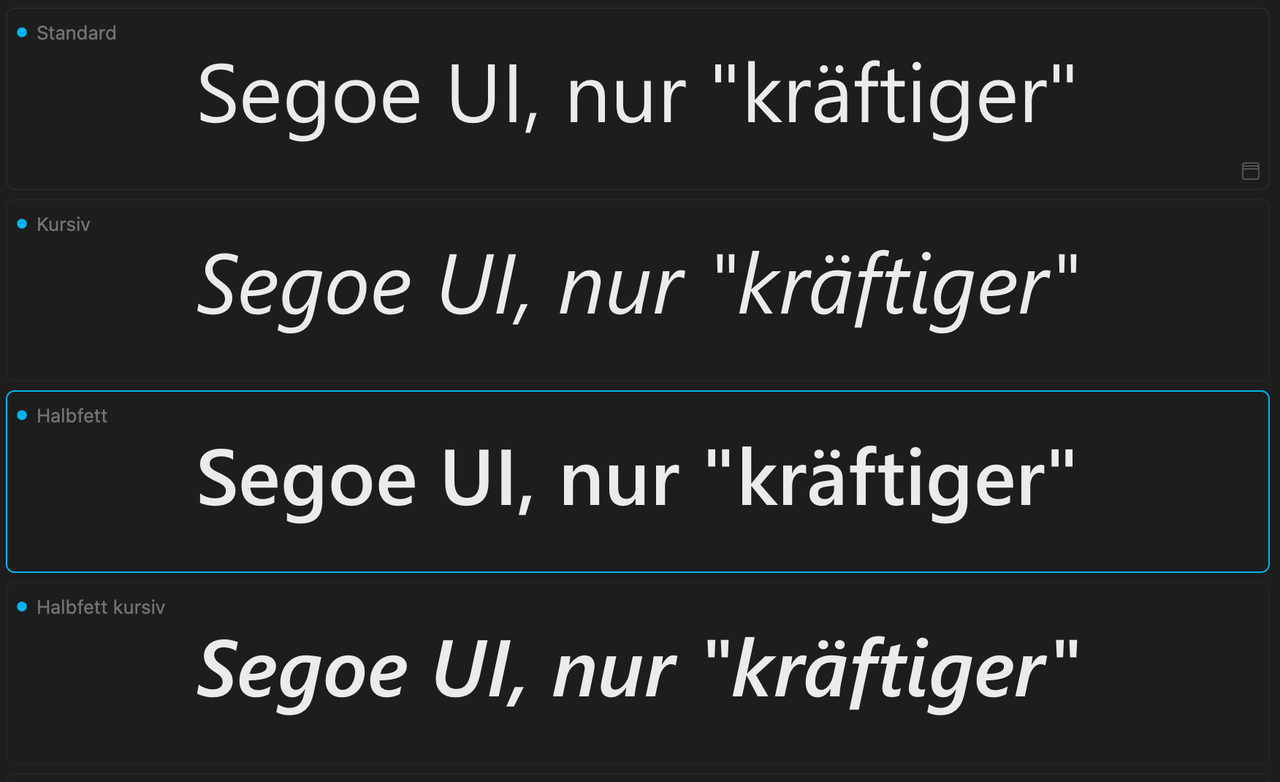
Segoe UI, nur "kräftiger"
wie die Überschrift vermuten lässt, bin ich auf der Suche nach einer Schrift, die der Segoe UI recht nahe kommt und insbesondere echte Kursive, nicht nur schräggestellte Zeichen hat, aber – sehr laienhaft formuliert – nicht so "blass" ist wie die Segoe UI.
Die SegoeUI gibt es ja in 6 Stärken: Light, SemiLight, Regular, SemiBold, Bold, Black
--> d.h. es müssten eigentlich für die Praxis genug Abstufungen vorhanden sein um das Schriftbild heller oder dunkler zu machen.
Die Frage ist vielleicht auch eher, wo sie "blass" wirkt.
Am Bildschirm (und dann: unter welchem Betriebssystem, das für die Rasterung verantwortlich ist)? Je nach Rastermethode kann das Ergebnis eher dünn und hell oder kräftiger aussehen.
Oder im Druck, und da: Laser oder was professionelles?
Alternativen:
Die Frutiger Next ist SEHR nah an der Segoe UI dran (man könnte sagen dass sie kopiert wurde). Und im Gegensatz zur alten Frutiger hat die Next auch eine richtige Kursive.
Auch die Myriad (und notfalls Pro) ist formell sehr nahe dran (man könnte sagen dass Myriad auch die Frutiger kopiert hat). Die hat sehr viele Gewichte, und sogar eine Variable-Font-Variante fürs Feineinstellen.
Etwas weiter weg, aber kommt darauf an was man so möchte: Open Sans.